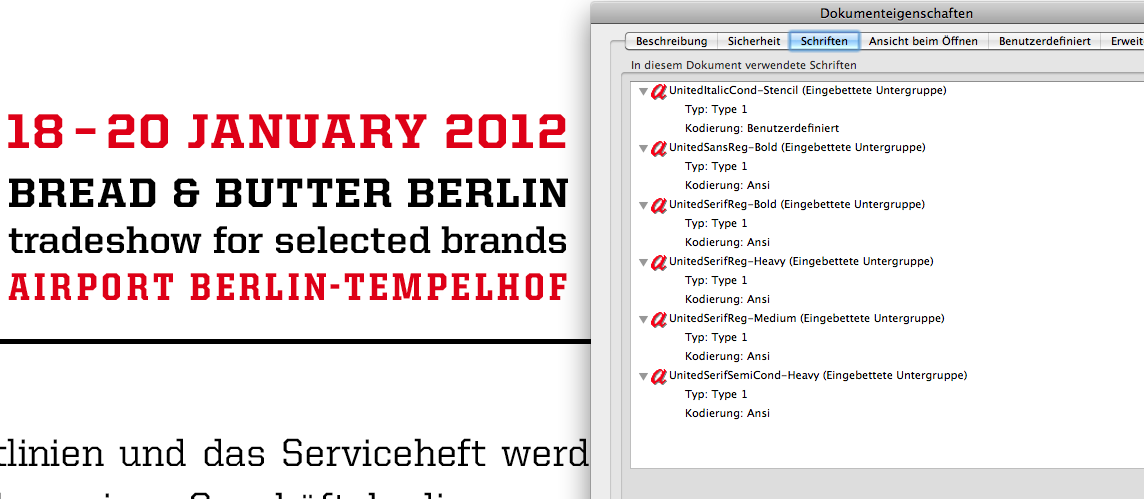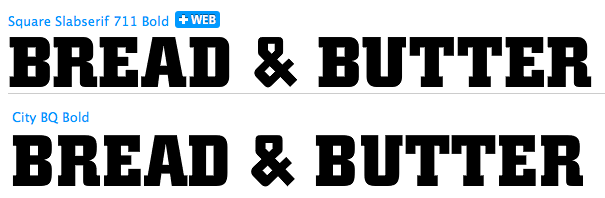
Messe Bread & Butter
Trick № 3:
hm, Kraut und Rüben. Im pdf werden andere Schriften verwendet als online, die goldene Unterzeile ist wieder eine andere … Square Slabserif könnte hinkommen.
jetzt müssen wir nur noch herausfinden aus was das krude logo ist.
[Edith fasst zusammen]
Logo/Unterzeile: Square Slabserif
Navigation: LTC Squareface
pdf: United Serif.
Das Logo ist aus der City Bold von Georg Trump gesetzt.
Weißt du das aus gesicherter Quelle? Ich würde es bei der Größe der Vorlage nicht sicher sagen können …
Nein, mit Sicherheit kann ich es auch nicht sagen. Da die Square Slabserif offensichtlich ein Klon ist, wollte ich lediglich auf das Original von Georg Trump verweisen. ;-)